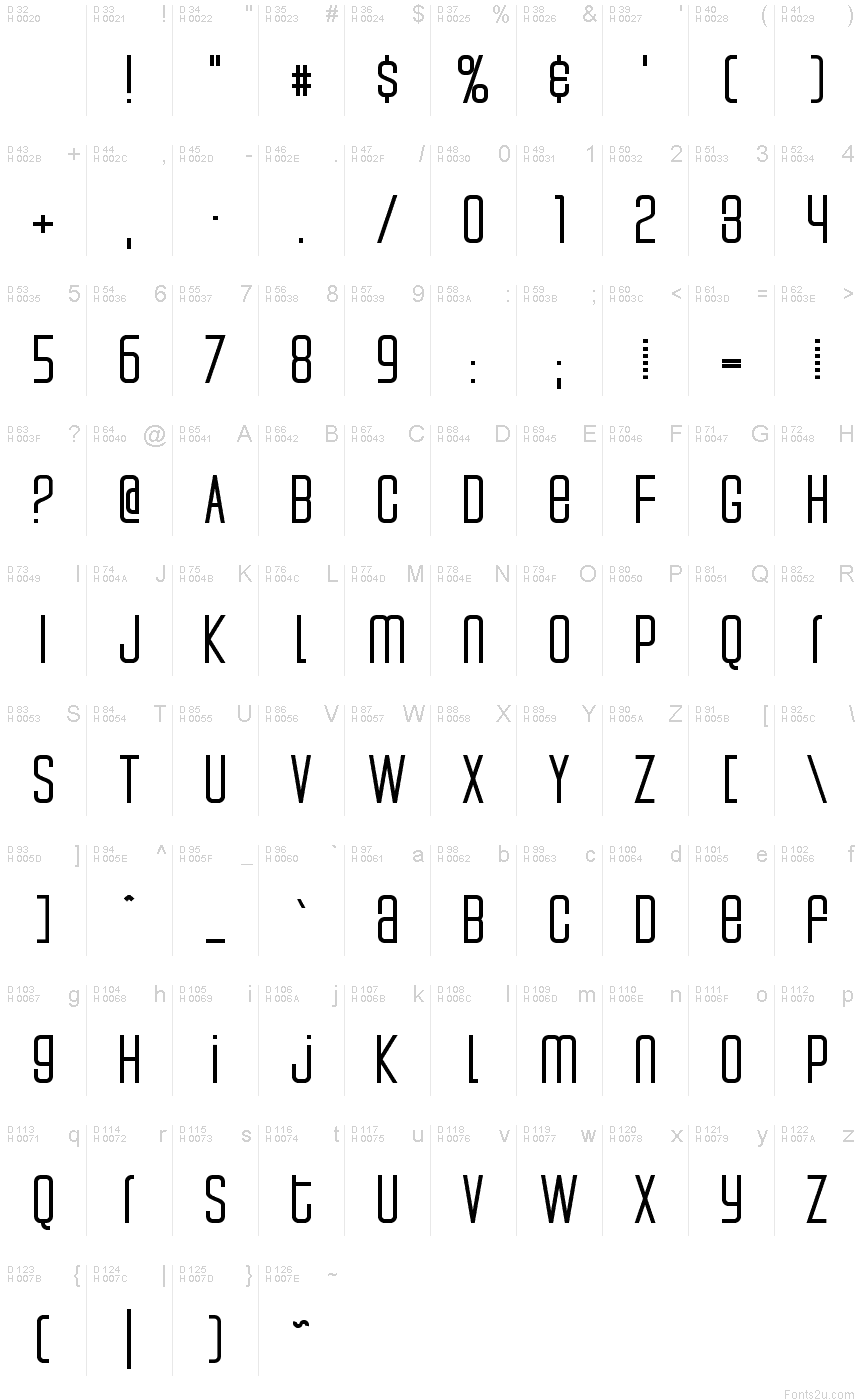
Weltron
Weltron od Font"a"licious Fonts to darmowy, retro-futurystyczny krój typu display o eleganckim, wczesnocyfrowym klimacie. Litery są wysokie i wąskie, łączą ostre, przypominające literę V złącza z miękko zaokrąglonymi narożnikami, co nadaje całości charakteru łączącego kosmiczną typografię z nurtem Art Deco.
Świetnie sprawdzi się na plakatach, okładkach płyt, klubowych ulotkach, w identyfikacji wizualnej technologii czy nagłówkach magazynów, wszędzie tam, gdzie darmowy font ma przyciągać wzrok stylizowanym, pionowym układem, zamiast zachowywać neutralność. Szczególnie dobrze nadaje się do krótkich tytułów i napisów, gdzie wydłużone kształty i zaokrąglone wcięcia nadają nawet kilku literom wyrazisty, syntetyczny rytm.